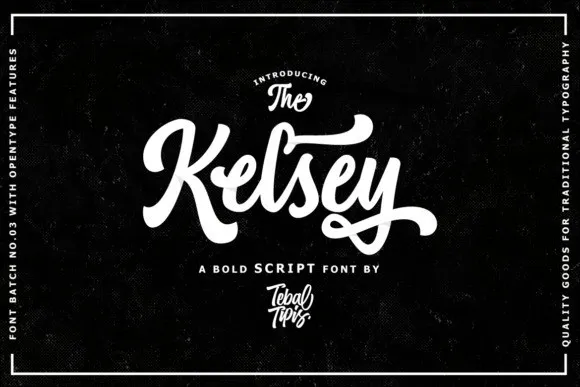
Kelsey Script Font é uma fonte script que traz consigo uma sensação natural, com linhas suaves e desenhos inspirados na escrita manual. Esta fonte foi criada para quem busca um estilo elegante e único em seus projetos de design gráfico. Com seu ajuste base variável, as linhas suavemente curvadas garantem que cada detalhe seja apresentado com um toque natural e cuidado. Além disso, a presença de PUA (Unicode Private Use Area) no Kelsey Script Font permite que você use todos os caracteres e alternativas disponíveis sem problemas. Seu estilo versátil faz dela uma escolha ideal para criação de cartões de convite elegantes para casamentos, arte de estação incrível e posts de mídia social capturando a atenção do público, além de muitas outras possibilidades criativas. Engane-se se pensar que Kelsey Script Font é apenas um detalhe adicional: ela pode transformar qualquer projeto em uma obra-prima.